字体设计绝不仅是一门简单实用的“制作”学科,历史文献的影响、工艺传统和排版技术的冲击、商业考量魂字、以及文化维度,很多因素都促使字体设计成为人文学科中的一个重要部分。
由于历史和文化的原因,拉丁字体的设计从理论到实践都达到了相当高的专业程度,西方设计师们在思考和作业过程中所体现出的严密的逻辑推演、对制作细节的极致关注,都值得我们中国的设计师借鉴学习。
如果说“设计”字体是一种解决问题的方式,那么“创作”字体则暗示了动态的文化关联、以及设计师在理解上下文语境中的角色。
那么,我们该“如何创作字体”?
创作动机
文字设计在平面设计中起着核心作用,如同很多职业一样,文字设计需要大量的训练以及对细节的足够关注。一名设计师设计字体,最初可能是源于好奇心或兴趣爱好,或是一些需求。每一个案例中的字体设计都是各有不同的设计目的,但大体可分成两种:专业设计和个人实践——一种是为了完成客户委托的商业设计,另一种则是缘于个人兴趣。
1.它的用途是什么?具体要求有哪些?需要设计哪些语言?安装在哪些操作系统中?有效区分基于设计的决策和产品的决策是有必要的,设计前要初步决策,构成设计方案。
2.另一个需要在设计之初就思考的,是该字体将被用于正文字体还是标题展示字体?正文字体必须更严格、更具有“奉献精神”,而标题展示体的要求则相对较低,易读性和遵循管理可因视觉吸引力而牺牲。
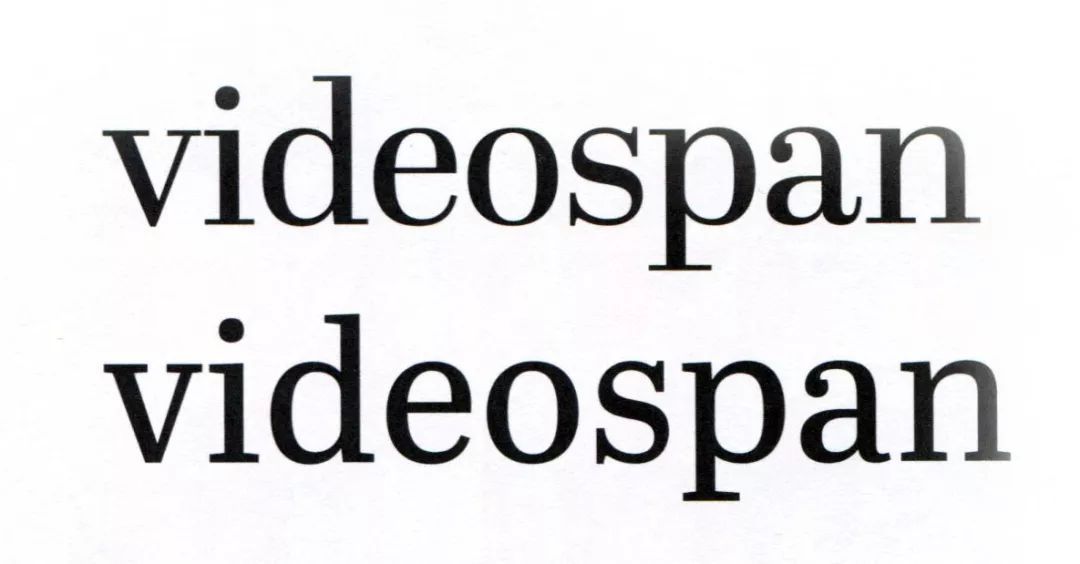
▲标题字体(上)与正文字体(下)之间的差异
假如字体是拳击手,那么正文字体要靠点数制胜,一场环环相扣的比赛任何微小的错误都是致命的;相对而言,展示体则是靠击倒制胜,几个字符足以吸引注意,并结果相当惊人。
过程方法
搞清楚创作动机后,就要开始进行字体设计。
首先就是绘制草图。画草图基本上有两种方法:纸上绘制,然后进行数字化;以及在屏幕上直接绘制。
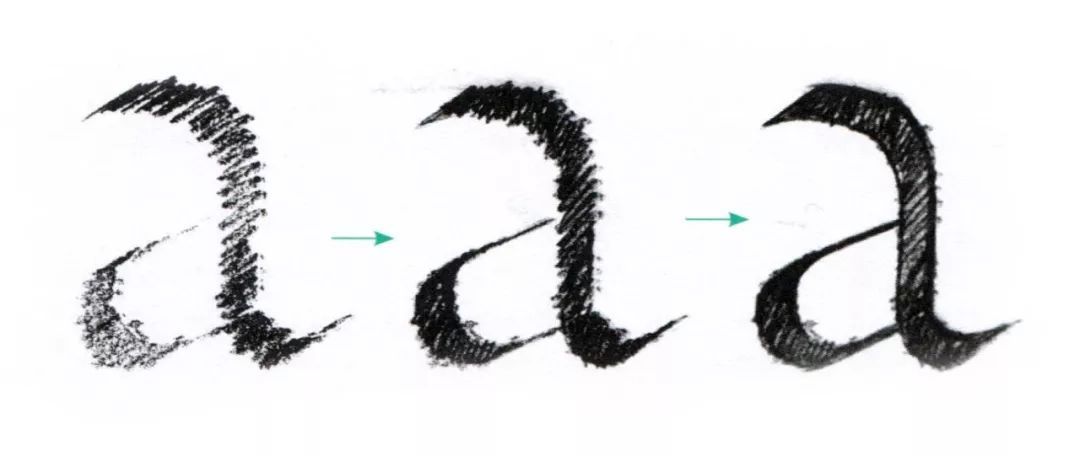
但即使字体是数字格式的,先用手绘仍然很重要。铅笔、白纸、不同粗细的黑色签字笔和硫酸纸,是设计师们的首选。
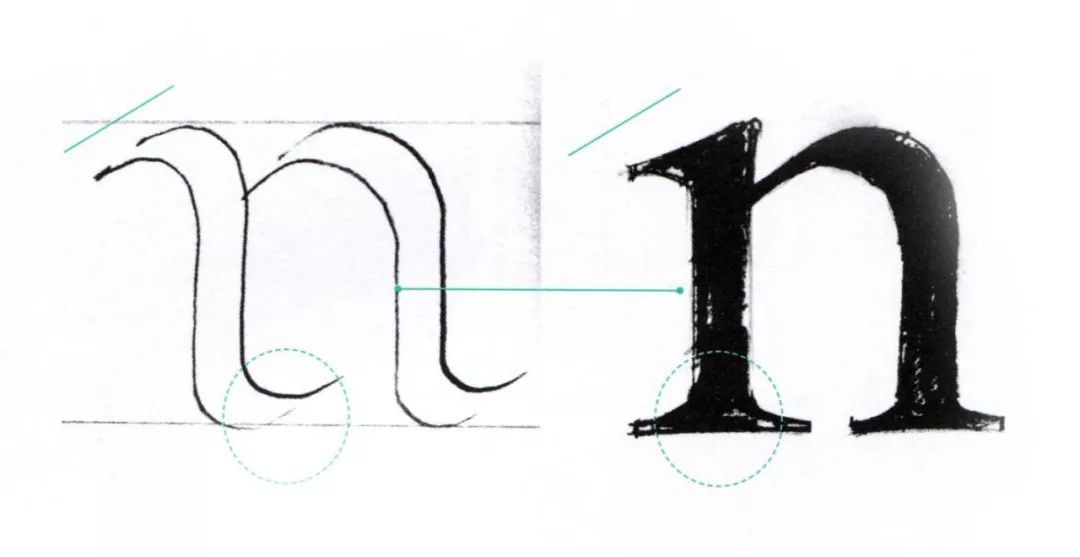
▲笔画的起笔处转化为衬线,收笔时在字符的底部形成双衬线
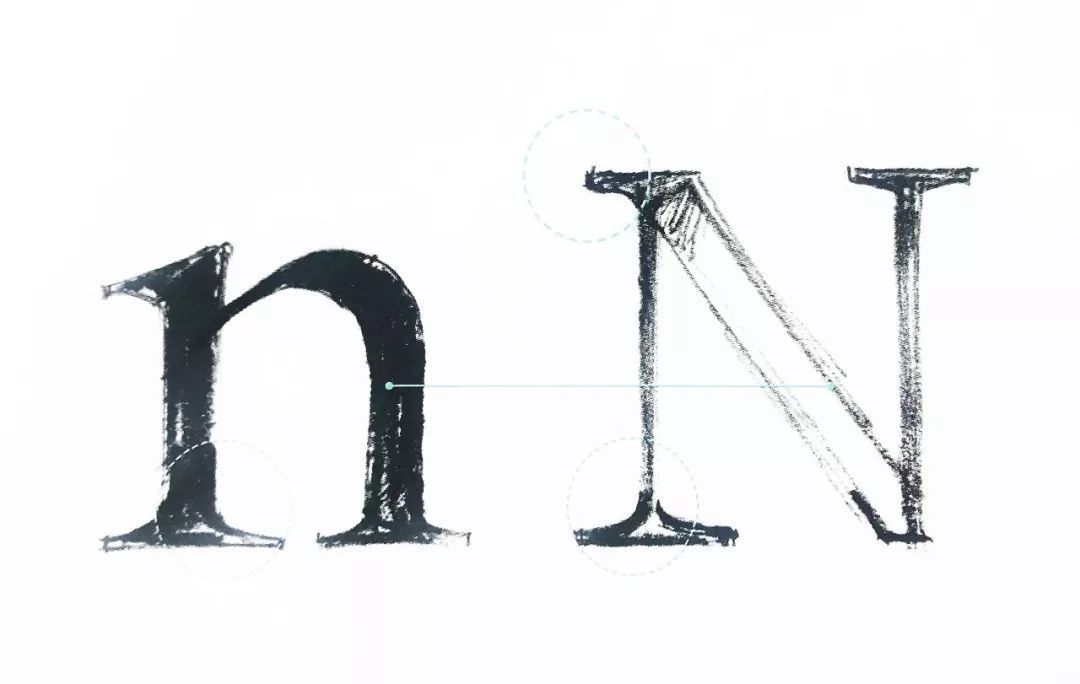
▲这些相似的衬线形式维持着大写字母与小写字母之间的关系
数字化
数字化是指将事先绘制好的形状——线条和曲线——以数字形式重建的过程。在数字软件中绘制曲线最常用的方法是用贝塞尔曲线。使用Illustrator、Photoshop等应用程序,以及专门用于绘制和生成的应用程序,如Fontographer、FontLab、Glyphs和RoboFont等。
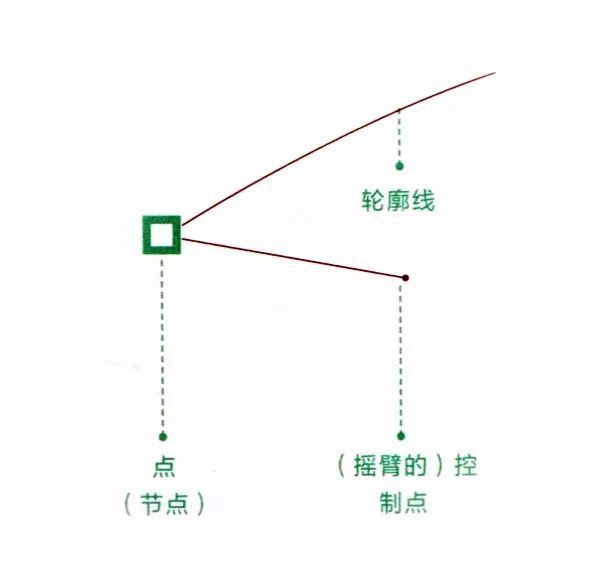
而对于将草图数字化的难点,就是确保能将手绘草图的本质完全呈现在屏幕上。
尺寸:在定义形状之前,有必要先定义字体的尺寸以及宽和高的关系,因为这些尺寸决定了字体的外观和功能。
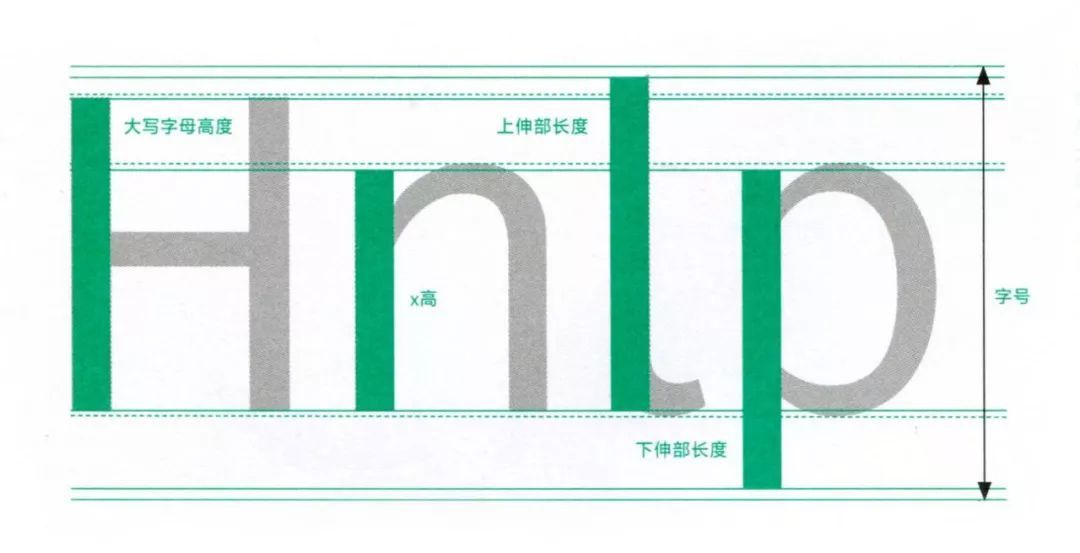
▲大写字母的字干应该稍粗一些,因为大写字母比小写字母具有更大的“字腔”,稍稍加粗以抵消大写字母内部的白空间
小写字母:我们可以从“n、o、v”这个顺序开始,因为它们符合基本的几何形状;随后再添加字母“a”,因为这个字母包含了关于这个字体最多的基因和信息。
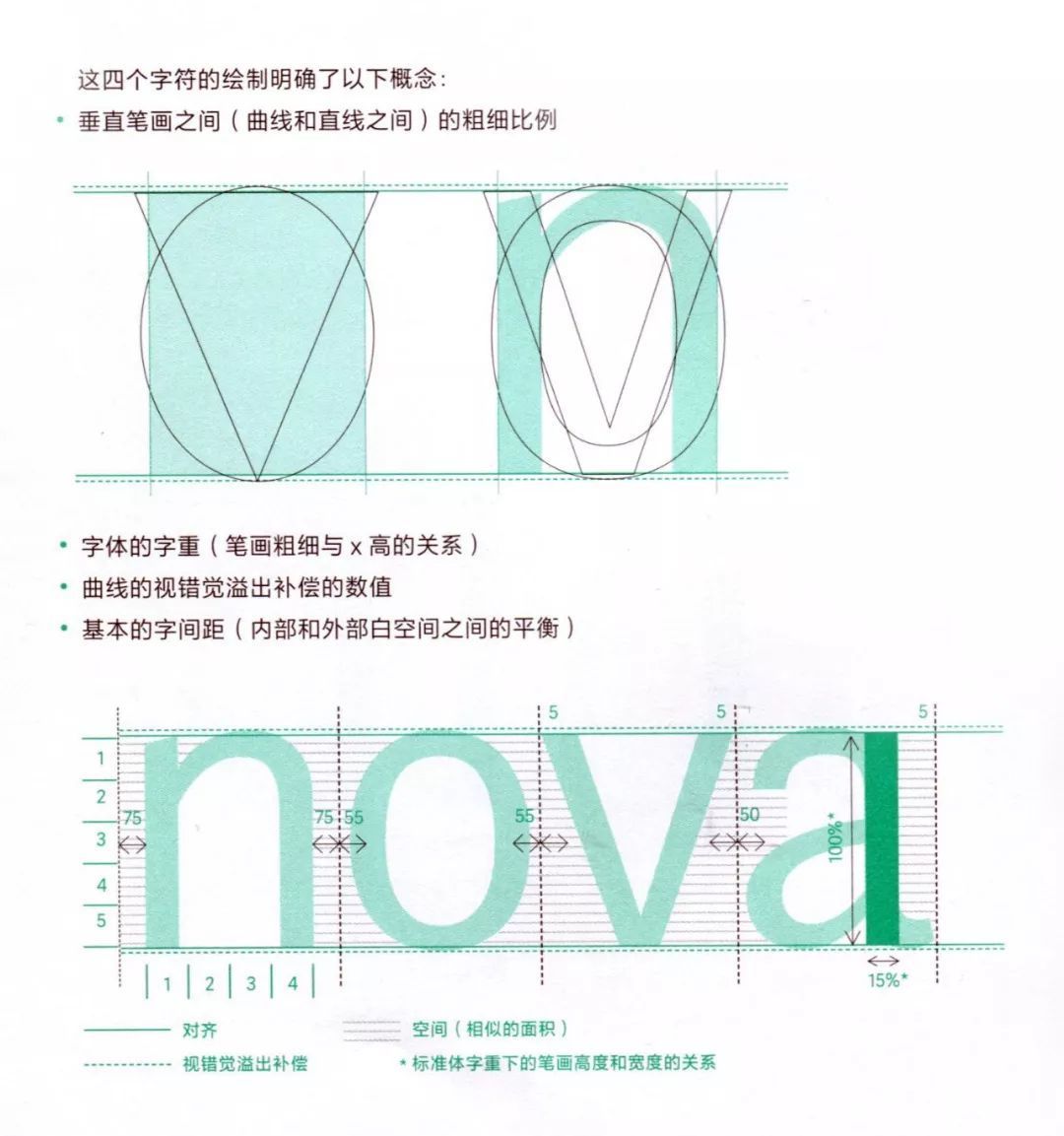
视觉调整:曲线为什么要有视错觉溢出补偿?因为当高度相同时,圆形和三角形看起来比正方形要小,因此,有必要补偿与这些形态相对应的字符,以使其与这些形态组相一致,使它们的高度看起来相同。
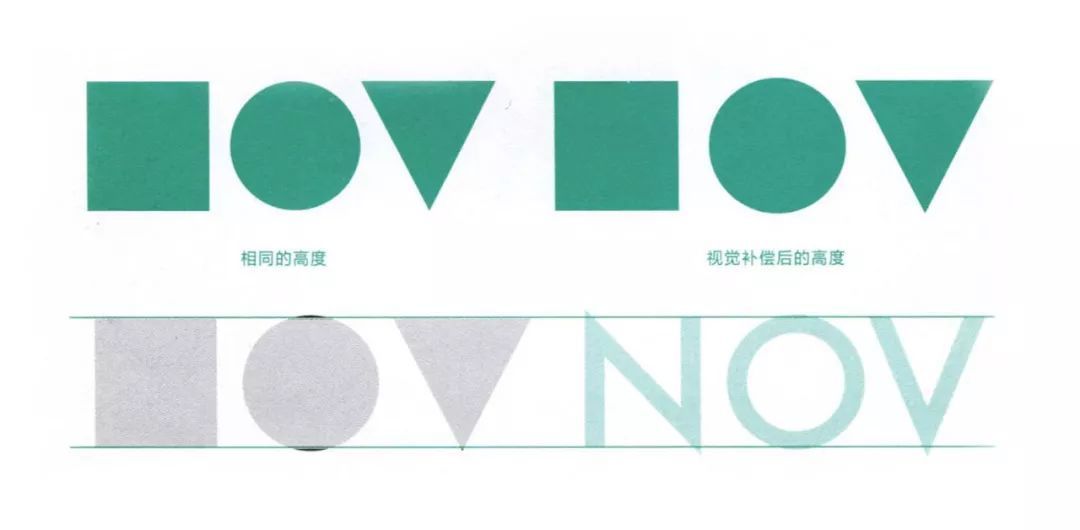
▲视觉调整的必要性
评估:鉴于字体设计的复杂和艰辛,随着工作的进程,有必要对其进行测试和评估。为此,我们使用“样本词”,它们会包含能明确其余字母表现形式的关键字符。典型的样本词有Adhesion、Hamburgerfontsiv和Handgloves。
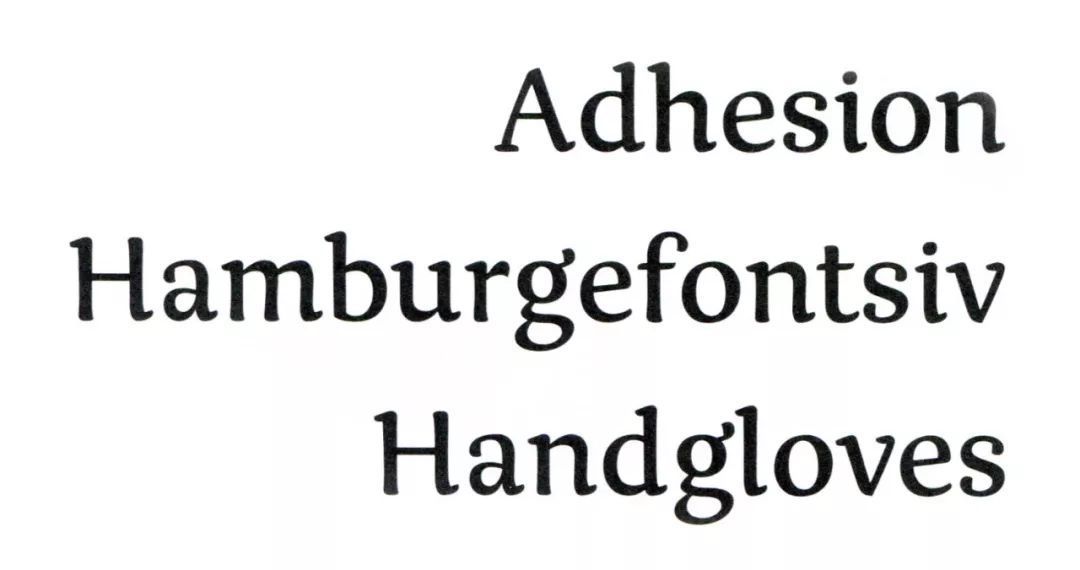
▲样本词
上面的内容,出自于今天要为大家介绍的一本书籍——《如何创作字体》。这是继《文本造型》后,又一本详细讲述西文字体创作干货的书籍。
著者
[墨] 克里斯托巴尔·埃内斯特罗萨(Cristóbal Henestrosa)
[西] 劳拉 · 梅塞格尔 (Laura Meseguer)
[阿根廷] 何塞 · 斯卡廖内 (José Scaglione)
译者
黄晓迪
审校
刘钊
这是一本追求在当代环境下描述字体设计,为字体设计书开创了新标杆的书籍。英国雷丁大学副教授,国际文字设计协会主席杰瑞 · 利奥尼达斯在推荐这本书时表示,这是一本通俗易懂、有信息量的书,结合了制作数字字体实践的深刻见解,以及字体设计师在设计思维和基本技能方面必要的诀窍。文字描述有亲和力,并辅以优秀的插图帮助读者学习。
这本书在西班牙语原版出版时,就备受关注,西班牙语原版由马德里: Tipo e 出版社于2012 年出版,之后各个国家争相出版了不同语言的版本。它的中文版由中信出版集团于2019 年出版,虽然较晚于其他国家的译本,但中文版是第一个非拉丁语言的版本,在亚洲更是第一个出版发行的语言。
“尽管书中的设计案例绝大多数来自拉丁文字,但可以将它看作适用于跨语言的字体设计的典范,这也是我们引进本书的重要目的之一。”编者刘钊表示。
/著者简介/
克里斯托巴尔 · 埃内斯特罗萨,出生于1979 年,本科毕业于墨西哥国立自治大学视觉传达专业,并在墨西哥韦拉克鲁斯的大学Gestalt 研究中心获得文字设计硕士和库珀联盟字体设计的学位。他的字体曾多次获得国际比赛的奖项,包括纽约TDC(字体设计比赛)和拉丁美洲文字设计双年展(Tipos Latinos)。他是Espinosa: Rescate de una tipografía novohispana(2005)的作者,也是墨西哥国立自治大学文字设计和字体设计教授。
劳拉 · 梅塞格尔,1968 年出生于巴塞罗那,是巴塞罗那的自由职业设计师和字体设计师。她专长于编辑设计, 从事与文字设计相关的各种项目,从字母组合设计、标志到定制字体。她在1992 加入了字库厂商Type-Ø-Tones,现在她与何塞 · 曼努埃尔 · 乌罗斯(Josema Urós)共同运营。2003 至2004 年间,她在海牙的荷兰皇家艺术学院学习了字体与媒体专业研究生课程。除了在出版物和国际展览中展现才华,她的字体设计也获得了很多奖项,包括纽约TDC 和国际文字设计师协会(ISTD)的奖项。她分别在Eina Escola d’Art i Disseny 大学和庞培法布拉大学设计学院(ELISAVA)教授字体设计和文字设计的研究生课程。此外,她还主持工作坊和写作。她是《TypoMag:杂志中的文字设计》(TypoMag: Typography in Magazines)的作者(索引书, 2010 年)。
何塞 · 斯卡廖内,1974 年出生于罗萨里奥,是平面设计师、字体设计师,与维罗尼卡 · 布里安(Veronika Burian)共同创办了字体厂商(TypeTogether),发布了许多获奖的字体家族。他在阿根廷布宜诺斯艾利斯大学教授文字设计,经常被邀请到国际会议和学术机构讲授文字设计并主持字体设计工作坊。何塞与豪尔赫 · 布恩 · 乌纳曾合著 《印刷术研究导论》(Introducción al Estudio de la Tipografía)。这本《如何创作字体》已经被翻译成包括中文在内的5 种语言。何塞从2013 年至2017 年担任国际文字设计协会(ATypI)主席。
一本通俗易懂、有信息量的书,结合了制作数字字体实践的深刻见解,以及字体设计师在设计思维和基本技能方面必要的诀窍。文字描述有亲和力,并辅以优秀的插图帮助读者学习。
——杰瑞 · 利奥尼达斯,英国雷丁大学副教授,国际文字设计协会主席
西文字体设计在计算机出现之前是特别小众的一个行业或职业,它所积累的很多专业知识和历史仅在行业内代代流传。计算机辅助进行字体设计之后,字体变得大众, 很多设计师进入设计字体行业(目前西文字体有几十万款)。这本书在字体设计的专业知识、技术更迭及营销模式几个方面均有建树,不仅对中西文字体设计师,还对平面设计师和客户有使用价值。
——王敏,长江学者特聘教授,博士生导师,中央美术学院学术委员会副主任国际平面设计师协会会员
数字媒介为字体设计提供了新的空间和命题, 需要设计师以多元的视角重估字体设计的时代价值和视觉意义。这本书不仅为不同语言字体设计的学习者梳理了清晰的脉络,同时指出了有效的路径和方法。
——何洁,清华大学美术学院教授
这本书通过“解剖式”手法,为读者揭示了拉丁字体设计的奥妙,既全面又深入浅出,尤其着眼于数字时代字体设计的最新技术手段的运用,从而使得这本书非常贴近当下,具有很强的现实意义。中国的字体设计师们固然以中文字体设计为中心任务,但他山之石可以攻玉,对这本书善加利用(而不是生搬硬套),将能触发我们开启中文字体设计教与学的新法门。
——仇寅,方正字库设计总监
这本书对于任何热衷于学习拉丁字体设计的人来说都是非常有用和有指导性的指南。它涵盖了基础知识,如字母结构、字间距和视觉校正等,以及更复杂的方面,如规划一个使用多基准字体设计的文字设计体系,以及如何进行小字号低解析度屏幕显示优化。我在我的字体设计工作坊中广泛地使用这本书,因为内容贴切,文章通俗易懂,初学者很容易入门。
——韦罗尼卡 · 布里安(Veronika Burian),字体设计师,TypeTogether字库公司合伙人
这本书首先对理解拉丁字体设计很有帮助,看似基础性的研究也包含着作者诸多实践经验、学术观点和图像例证,这在本质上也会为我们解析汉字文字设计提供新思路。汉字的历史或现代性对汉字文字设计提出了问题,我们又如何厘清新语境下设计的普遍性方法和问题独特性的关系?而这本书讨论设计细节的态度和方法也比较有意义。
——王子源,中央美术学院设计学院教授,世界设计组织联合会(ico-D)副主席(2015 — 2019)
字体设计和文字标识设计在企业识别中扮演了越来越重要的角色,特别是在数字媒体和互联网时代。这本书阐述了字体设计、字体销售、字体版权,以及企业识别设计中渐渐被大家熟知的定制字体等方面,我相信这本书对于委托设计或购买字体的客户、字体的使用者(设计师)、字体的设计者都是具有启发意义的。
——解建军,东道品牌创意集团董事长,中国广告协会副会长,中华商标协会副会长,德国国家设计奖(2015 — 2018)评委